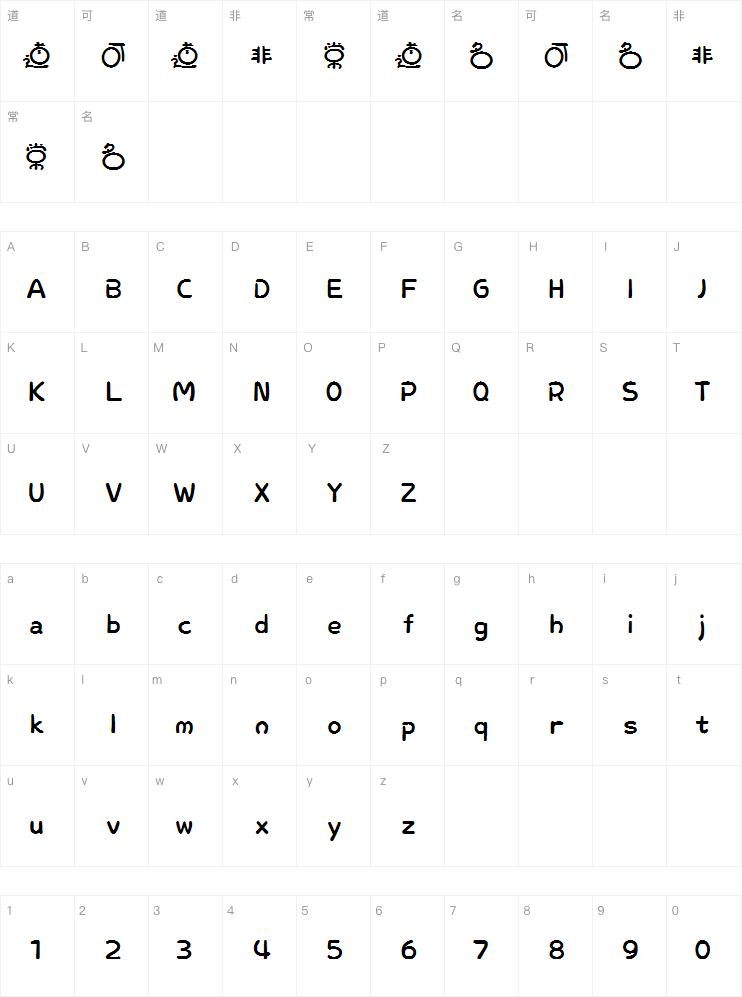
上首泡泡手写体,中文约6763字。这套字体以 “把汉字揉成软泡泡” 为设计锚点,在保留汉字骨架辨识度的基础上,将所有笔画的棱角替换为饱满的圆弧 —— 起笔如轻按的海绵,收笔似吹起的气泡,连转折处都做了 “软弹过渡”,让每个字都像刚从笔端 “浮起来” 的蓬松形态,既避免了机械感,又强化了活泼灵动的视觉气质。